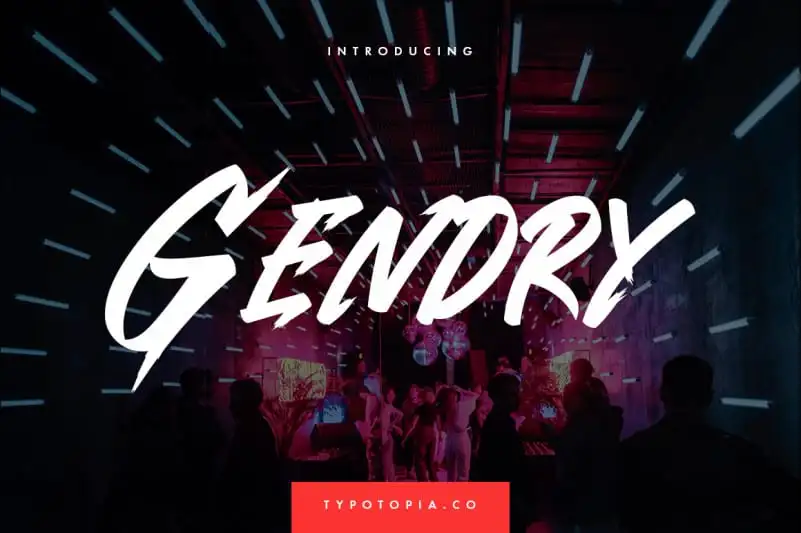
Gendry Brush Font – Fonte Grátis
Gendry Brush Font
A Gendry Brush Font é uma linda fonte desenhada à mão, com traços suculentos e grosso. Suas letras são ideais para adicionar um toque de alegria aos seus trabalhos de design. Essa bela fonte exibicional será perfeita para incorporar em todas as suas idéias criativas, destacando-as ainda mais. A Gendry Brush Font é uma excelente escolha para aqueles que desejam dar um ar descontraído e divertido a seus projetos. Com apenas algumas palavras da fonte, ela pode transformar qualquer ideia num design irresistivelmente encantador. Seja para criar cartões de convite especializados ou capas de livros originais, a Gendry Brush Font é uma escolha certa para quem valoriza um toque único e colorido em seus projetos visuais.